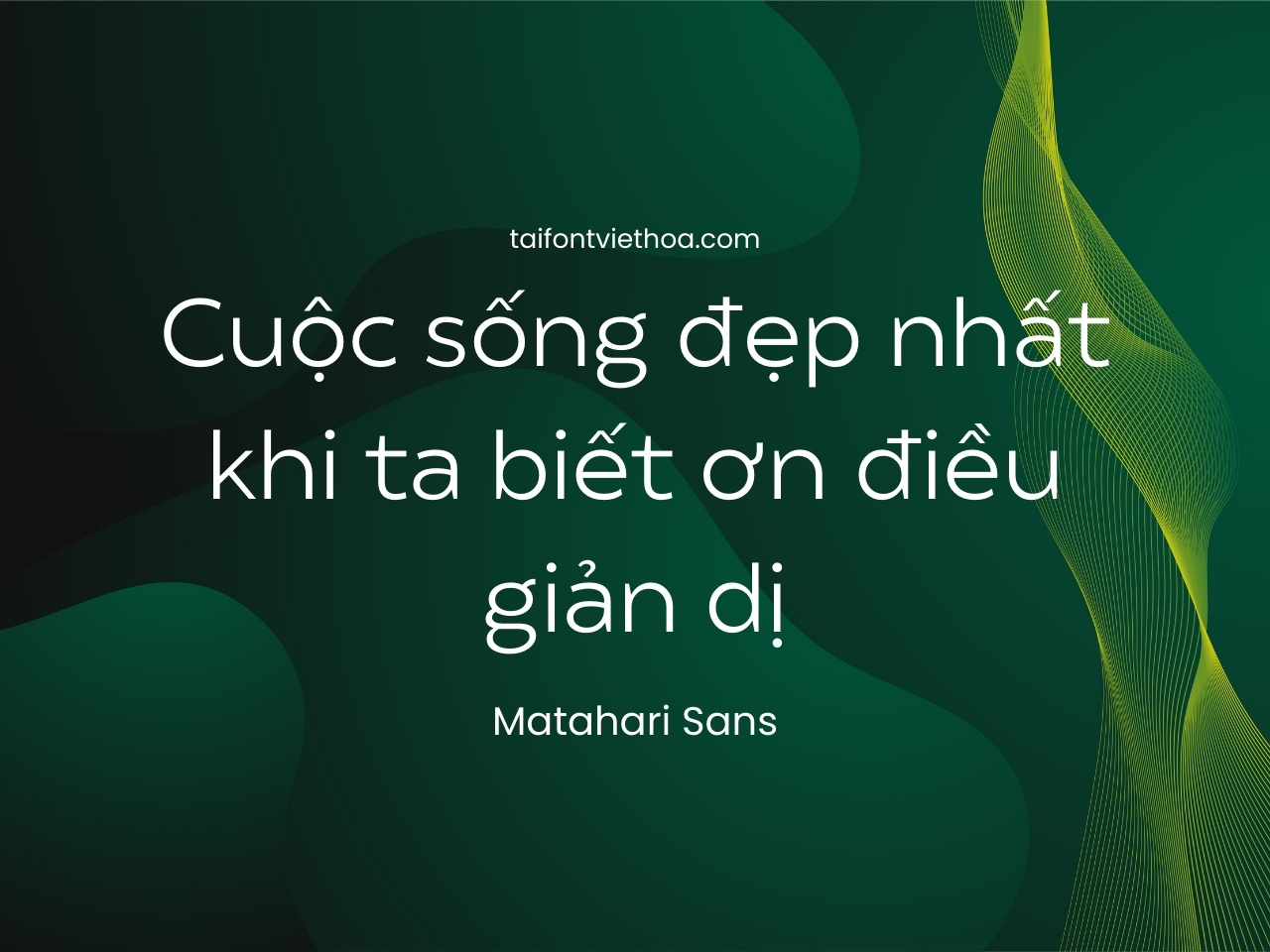
Font việt hóa Matahari Sans Family đầy đủ Font Tiếng Việt
Giới thiệu về font Matahari Sans và bản Việt hóa
Matahari Sans là một bộ font sans-serif hiện đại được thiết kế bởi Sundance Tipografia – một studio font nổi tiếng với các thiết kế mang tính thực dụng nhưng vẫn đảm bảo tính thẩm mỹ cao. Font được phát hành như một family đầy đủ với nhiều trọng lượng từ Thin đến Black, thích hợp cho cả tiêu đề và văn bản. Phong cách thiết kế của Matahari Sans lấy cảm hứng từ các font grotesk cổ điển và hệ thống lưới thiết kế Thụy Sĩ, tạo nên một kiểu chữ mạnh mẽ, sắc nét và linh hoạt.
Bản Việt hóa của Matahari Sans được thực hiện bởi chính Sundance Tipografia, hỗ trợ đầy đủ tiếng Việt và hơn 85 ngôn ngữ khác sử dụng bảng chữ cái Latin mở rộng. Các ký tự tiếng Việt được tích hợp chỉnh chu với diacritics đẹp mắt, giúp đảm bảo khả năng đọc và độ tương thích khi dùng trong các dự án tại Việt Nam. Font này đã được taifontviethoa.com sưu tầm, chọn lọc và giới thiệu đến cộng đồng thiết kế trong nước, phục vụ đa dạng nhu cầu từ in ấn, digital đến thương mại điện tử.
Phong cách hiện đại – Cấu trúc chuẩn và dễ ứng dụng
Matahari Sans sở hữu cấu trúc sans-serif hình học rõ ràng, với các đường nét mạnh mẽ và đồng đều. Font có hệ thống trọng lượng đa dạng, phù hợp với các layout thiết kế phức tạp, từ in ấn brochure, trình bày báo cáo đến giao diện UI/UX và thương hiệu. Các chữ cái có hình dáng cân đối, độ rộng vừa phải, dễ đọc ở mọi kích thước. Ngoài ra, font còn cung cấp ligatures và các ký tự thay thế để mở rộng khả năng thể hiện sáng tạo.
Font này rất phù hợp cho các ngành như công nghệ, bất động sản, startup, giáo dục, thời trang hiện đại và hệ thống thương hiệu chuyên nghiệp. Ngoài ra, Matahari Sans còn là lựa chọn tối ưu cho các chiến dịch quảng cáo, thiết kế bảng hiệu và nhận diện logo nhờ khả năng truyền tải sự chắc chắn, đáng tin cậy và hiện đại.